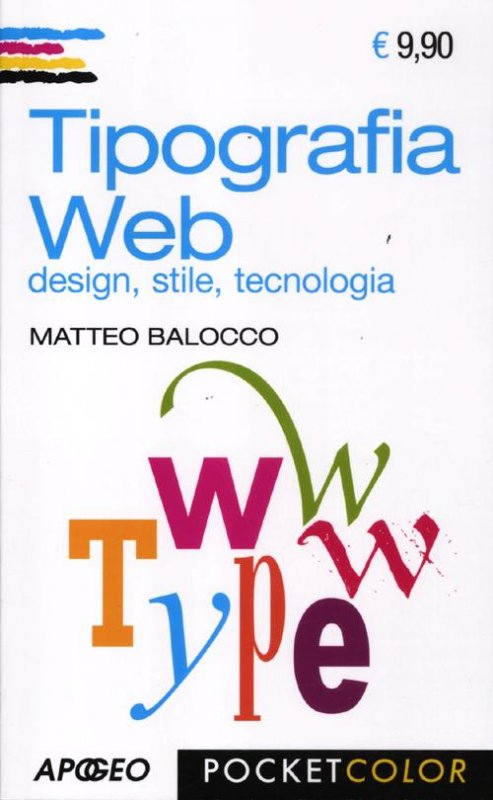
Scegliere la forma e l'aspetto di lettere, parole, paragrafi, significa progettare il modo in cui appare e viene letta una pagina. Se il ruolo e l'importanza del carattere tipografico sono noti e vantano una lunga tradizione nei media stampati, è solo negli ultimi anni che si è vista un'evoluzione analoga anche in rete. Oggi abbiamo accesso a un'incredibile varietà di caratteri progettati specificamente per il web, disponiamo di metodi efficaci per incorporare font nei siti, siamo abituati a utilizzare applicazioni la cui identità è definita in modo quasi esclusivo dalla tipografia. Si moltiplicano le possibilità, si moltiplica la complessità, diventa sempre più importante fare scelte consapevoli e significative per ogni progetto. Questo tascabile distilla, organizza e fornisce i punti di riferimento essenziali per orientarsi tra colori, caratteri e punteggiatura, offrendo risorse, tecniche ed esempi.
Tipografia web. Design, stile, tecnologia
| Autore | Matteo Balocco |